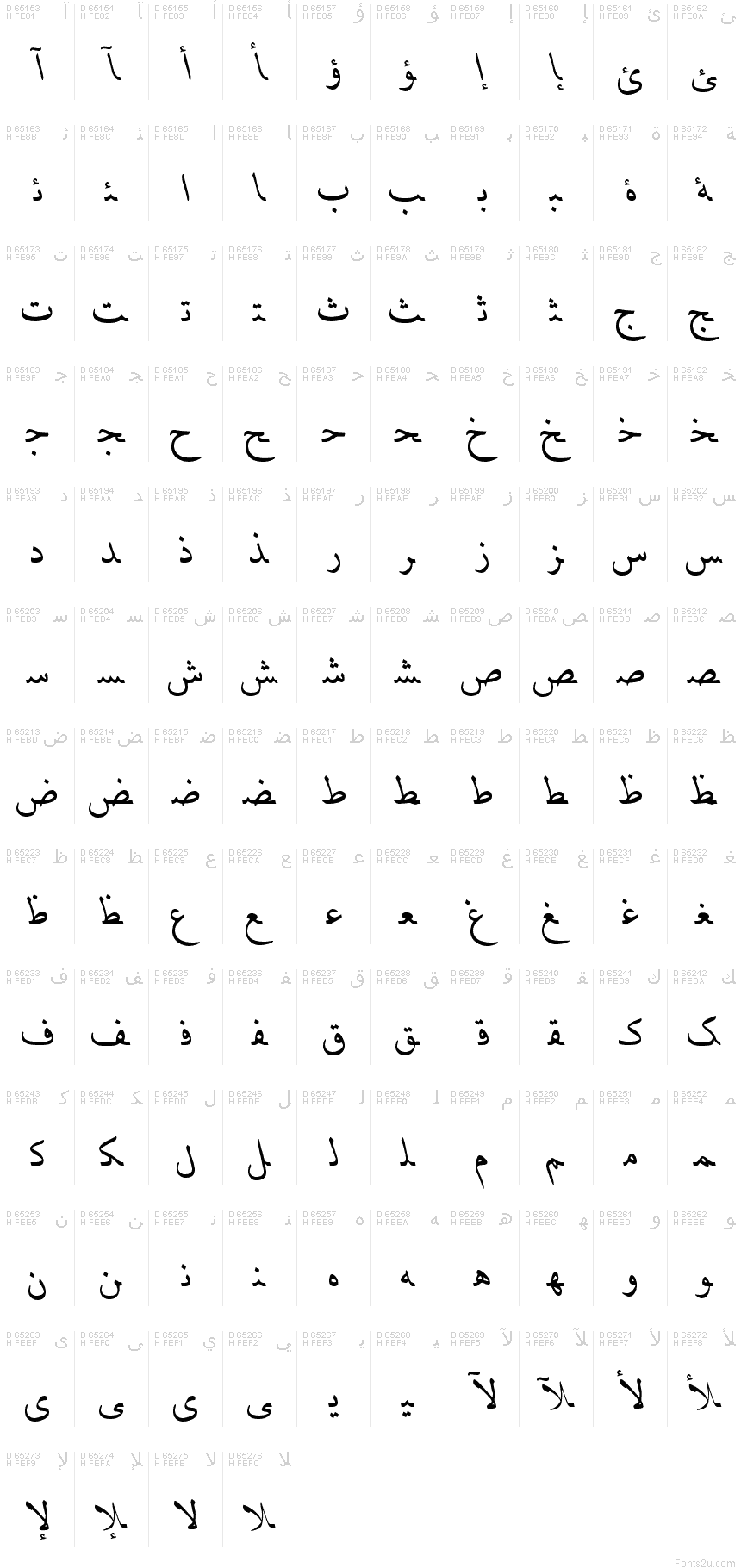
B Tehran Italic di Borna Rayaneh è un font arabo display gratuito, caratterizzato da tratti inclinati e netti e da curve superiori arrotondate che conferiscono alle lettere un aspetto rapido e vivace. Le forme appaiono meno formali rispetto agli stili più dritti della stessa famiglia, offrendo un maggiore senso di movimento su ogni carattere.
B Tehran Italic è perfetta per manifesti culturali, branding di ristoranti, copertine di libri, packaging e grafica editoriale, contesti in cui questo font gratuito riesce a trasmettere energia e personalità ai testi brevi. È particolarmente efficace nei titoli e nelle intestazioni, poiché il ritmo angolato mantiene dinamiche le parole senza risultare troppo rigido.